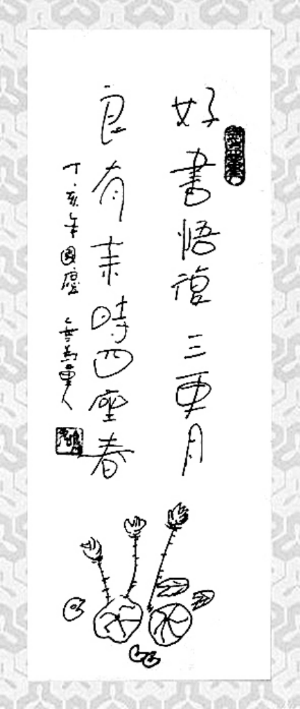
陈建明:南部“童体书法家” 写字就像捉迷藏
导语据新华社报道,2008年4月,南部县青年书法家陈建明与北大方正电子有限公司签约,将其独创的一种新型字体,以电脑编码的形式,收入北大方正字库,广泛应用于广告、卡通、QQ聊天、报纸印刷等。陈建明独创的童书,是一个充满童稚色彩的文字世界。汉字的偏旁部首,在他的
据新华社报道,2008年4月,南部县青年书法家陈建明与北大方正电子有限公司签约,将其独创的一种新型字体,以电脑编码的形式,收入北大方正字库,广泛应用于广告、卡通、QQ聊天、报纸印刷等。
陈建明独创的童书,是一个充满童稚色彩的文字世界。汉字的偏旁部首,在他的笔下,似乎都化成卡通人物,游走争斗,嬉笑怒骂,栩栩如生。他在枯躁严谨的文字世界和轻松幽默的现实生活之间搭建了一座桥梁,第一次将严肃正统的书法艺术童趣化。
童体书法家:陈建明
陈建明创作的“童书”
南部书法家京城“赶考”
2008年4月,北京。
“你的书法我们认真看了,有个性,很特别。但是我们需要对许多技术环节进行认定和评审,你能配合吗?”北大方正一位高层人士与陈建明见面的第一句话,充满着对他能写出如此诙谐幽默、极具童趣意味的字体心存疑虑。
这是陈建明平生面临的第一次书画艺术“大考”。从南部老家赶到京城,这位年过不惑的川北汉子一咬牙:拚了!只有充分展示,尽情发挥,才能把自己耗尽心血潜心苦研数年的书法艺术,公之于众,获得认可和推广。
“练习书法不必总是那么提腕顿笔,枯躁乏味,它还可以像捉迷藏一般悬念迭出,充满乐趣。”陈建明说,他创造童体就是为适应现代人轻松、乐观的生活态度和方式,把书法艺术大众化而作出的一种努力。如果这种努力获得认可,那么,将有更多的童体字体使用者被他带入一个轻松、童稚和充满浪漫气息的文字世界。
北大方正字库是最大的电脑汉文字库。陈建明此番如约赶赴北京,除了几支笔和一些字画作品,他什么也没带,什么也不需要带。他把自己的这些书画展示给专家,任由他们品评。
见面会接束后,陈建明就被安排到宾馆住下,工作人员给他一些纸,让他现场写字。开始在普通白纸上写,接着就在熟宣上写,再在生宣上写。每写好一张纸,就由工作人员拿走,送给专家观瞻。
经过多轮考试和评价,专家们终于认可了陈建明独创的这种童体。全国信息技术标准化技术委员会副秘书长王立建说,他第一眼见到陈建明的“童体书法”时,觉得很有个性。但是这种字体究竟有没有电脑开发潜力,有没有市场前景呢?这个问题必须要经过专家评定。在一次全国的信息技术标准化会上,他向一些专家推荐了“童体书法”,大家都认为这种个性化的字体应该有很多人喜欢,因为现在是一个个性时代。但要让书法字体进入电脑字库还有一个过程,必须由书法家和电脑工作者紧密合作,规范书法家书写的随意性,经过编码后就可以将书法作品变成电脑可以识别的字体。
王立建说,陈建明的“童体”,除了其艺术价值外,最重要的就是市场价值,看看这种字体究竟有多大的使用范围和频率。
在多轮评审后,陈建明的“童体书法”,终于被北大方正字库同意录入。字库一位高层在与陈建明签完合作协议时说,很显然,这种“个人书法用品开发成电脑识别的字库很罕见”。
备受网络疑质的“童书”
然而,这种“童体”字一面世,并不总是受人欢迎的。关于“童书”的争议,最早是从天涯论坛开始的。当时,一位叫“憨豆叔叔”的网友把陈建明创造的童体书法作品放到论坛里,引起网友的重点关注。
“我儿子看了第一句话就是:给人一种搞笑的感觉。”网友冬日暖阳519说,“我个人认为这种字体确实极有童趣,看字如看画,字画为一体,给人一种休闲随意但又带有艺术美感。作为一种字体立足于书法界,并不一定非要墨守成规,就好比现代的涂鸦比传统的国画还要走俏。虽然欣赏感强,但要推广个人认为不太容易。”
“可以设想,随着童体字的广泛运用,这种字体可能进入中小学生的习字课本。因为这种字体本身就好似为儿童写字而创立的。书画本同源,童体颇具象形字的特征又兼童趣的魅力,可以开发中小学生的智慧,又能使中老年人在习字中获得身心的愉悦,实在是一件大好的事情。”网友心之星空说。
而相当的网友在肯定陈建明的“童书”有“情趣”的同时,并不承认这是一种独立的字体。有些网友称陈建明的书法只是一种美术字,不能自成一体;有人甚至认为陈建明所创造的童体,对汉字书法是一种“伤害”。
童体到底是一种什么样的字体?童体是并列于大篆、小篆、甲骨文、金文、隶、行、草、楷书体还是某一种字体的变体?还是兼容多家书体基础之上的独立字体呢?抑或只是某一个书法家的个性字体?据“憨豆叔叔”介绍,面对童体,网友们有太多的疑问和好奇。
但是更多网友认为,几千年来,汉字在演变和发展过程中,每个历史时代都有每一个历史时代的书法字体艺术流派和风格。古老文明与现代文明发展至今,是躺在前人的基础上一成不变呢?还是要有所创新、有所发展、适应现代多元化社会并存和发展的需要,改变人们现有的审美认识?当越来越多的人用电脑代替手写,汉字字体的演变是不是就止步不前了呢?
“点”与“圈”构造的“童书”
陈建明留着平头,圆圆的脸,说话总带着笑。但他为人低调,采访他的媒体又多,因此与他约谈也不是易事。7月12日下午,我们早早赶到南部县城,在嘉陵江边选了一个茶馆坐下,打电话通知他见面。谁知他不冷不热地说,现在是午休时间,等午休结束后,他还要去单位请假。下午6时后,他有一个雷打不动的习惯——骑5公里单车,再到嘉陵江游泳健身,寒暑不歇,长年坚持。
但是,真正出现在记者面前的陈建明,只需两三句话,就让人感觉到他待人的热诚和对书法艺术的精深素养。
陈建明生于1963年,早年供职于企业。1990年,因为有书法特长,被调至县文化馆工作。1992年,抱着良好的创业梦想,他离职下海,在沿海媒体当过记者。
媒体的从业经历,让他具备了一定的社会关系。1994年前后,他进入宋庆龄基金会江西分支机构,先后参与成立了3家公司。1995年,他进入北海一家星级酒店,作副总经理。
长期在外奔波,无暇照顾家庭,陈建明婚姻出现变故。1996年,陈建明从南方回家,处理完毕失败的婚姻之后,他的工作已从文化局调至人事局,这使他放弃了继续下海的打算,决定在家一边研究书法,一边抚养儿子。
2000年起,身为四川省硬笔书法家协会常务理事、南部县硬笔书法协会副主席的陈建明,在吸收传统书法艺术精髓的同时,开始有意识地创新,走一条自我发展之路。
“汉字能不能写得更有趣一些?”具有绘画功底的陈建明,觉得把书法艺术进一步跟绘画相通相连,或许会有一些收获。一次一位好友来访,陈建明边写字边让他提意见,好友想了半天,说:“汉字书法已有几千年的发展历史,你摹仿古人字体,看起来气势充足,但无趣味,都是一些没有个性化的方块。”朋友的意见一直让陈建明难以释怀,汉字能不能写得像漫画一样,让人发笑,让人捧腹,充满童趣?
陈建明开始对每个字体进行有意地夸张和变形,逐渐演练出一种新的字体,其笔迹圆润洒脱,极富童趣和美感。
“我对童体有两个原则,第一是简便,遇方则圆,最好一笔写成,省事省力;第二是象形,还原象形字的图画本质,把指示字与会意字也力争按象形字的表达效果进行夸张。这样,基本上每个单独的字,都具备一种表情了。”
“陈叔叔写的字都像在唱歌!”陈建明按照自己对“童书”的理解,写出许多书法作品,然而把这些作品拿出去展览,他的字经常逗得小朋友们忍俊不禁。但陈建明想,人类的感情不只是笑和唱歌,童体还可以表现出丰富多变的复杂情感。于是,他开始对一些基本笔划进行抽象变形后,又进行归纳和总结。
“我最后发现,在书写过程中,点可以表示横、也可以表现撇和捺。而方框可以简化成一笔写就的圆,圆的不同形状出现在同一个字中,会产生不同的审美感受。在书写的时候,也不一定要按传统的从上到下,从左到右,也可以从下到上,从右到左,率性而为。”陈建明专门制定了26句四字歌,对童体字的书写特点进行规范。
“龙奥图”为北京奥运助威
为了让童体字得到更大的推广,也为百年奥运奉上一声祝福,陈建明决定用童体字制作书法作品讴歌奥运。
北京申奥成功后,他决定发挥自己的书法特长,创作书法作品为奥运会增辉。为此,他参阅了大量资料,先后构思了100多幅书画作品,但始终感到不满意。今年初,陈建明特意到奥运村采风,寻找灵感。当看到宏伟壮观的鸟巢、水立方后,他一下找到了感觉:决定创作一幅龙奥图,图的主体是一条腾飞的中国龙,象征祖国的繁荣昌盛,飞龙本身就是一个草书的龙字,由56个奥字组成,它们分别代表我国56个民族。56个奥字中,44个奥字选用俄、英、法、德、日、韩、西班牙等国的“奥”字,12个奥字选用汉字的楷书、隶书、甲骨文、金文以及部分少数民族文字组成。
2008年3月17日下午,陈建明采取竹签与软笔相结合的方式绘成龙字骨架,一个礼拜后,他将把56个奥字装到龙字内。整个龙奥图长约1.4米、宽约1.2米。整幅作品由红、黄、黑为主色,红色象征着国运昌盛,寄寓欢迎世界体育健儿和人民来中国作客之意;黄色为高贵之色,象征着丰收的喜悦,展示着中国改革开放的成果;黑色喻意稳重,象征着中国事业稳步向前推进。据陈建明介绍,此作品已通过相关渠道,送往北京参加奥运书画巡回展。
此前,2004年小平同志百年诞辰,陈建明创作了一幅万言百米书法长卷,并开展了万人签名忆小平活动。他的想法是:晚年的小平既是受中国人尊敬的领袖,又是一位平和充满童心的老人,他的声音行走,都洋溢着返璞归真的气韵。歌颂小平的书体,为什么不能从古人的书艺返回童真呢?于是他用童体书写了长卷的大部分内容。当时,中央电视台、中央人民广播电台、央视论坛等全国多家媒体进行过报道。此时,童体书法第一次为人们广为知晓。2005年8月,陈建明荣获迪尼斯中国总部颁发的“中国专题书法之最”证书。
2006年,在共和国红军之父——朱德元帅诞辰120周年之际,陈建明特意创作《百德图》,缅怀朱德总司令,倡导诸家说“德”。
从《百德图》到龙奥图,陈建明借助一个个特殊的书法载体,诠释着他对艺术、对人生、对社会政治生活的热爱和颂扬。他也通过这些书法创作,一点点地扩大童体书法的知名度,让这个艺术领域的新生婴儿,通过社会的评价和认同,逐渐走向完善。
“现在是一个网络时代,即使是生命力旺盛的传统书法艺术,也离开不网络的流传。”陈建明说,把网络与书法艺术相融,成为他探索书法艺术传播途径的切入点。因此,他从1996年自费开办一个纯书画艺术的网站以来,他已有10多年网络编辑经验。而这个网站,目前已跻身全国书法百强网站。“通过这个网站,我已在全国范围团结和培养一大批书法艺术爱好者,这些人,将是童体书法推广和升华的中坚力量。”